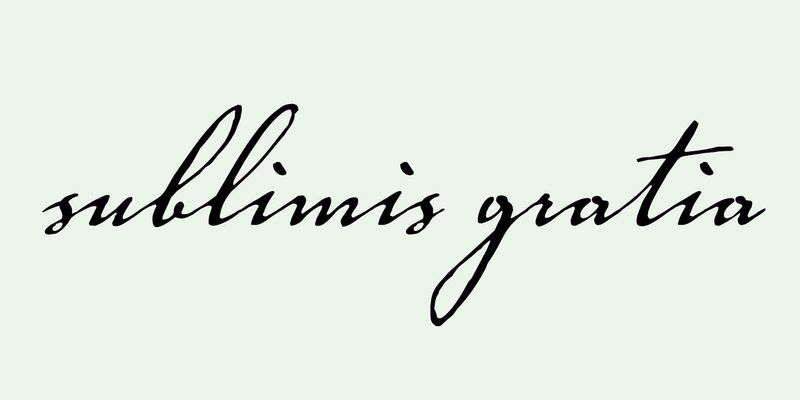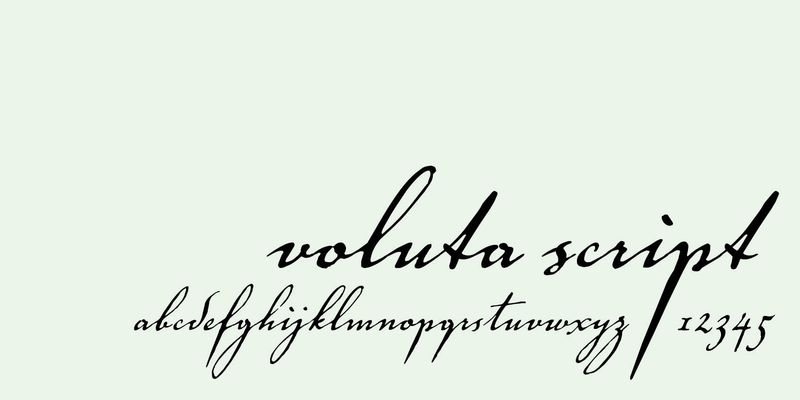
Австрийский дизайнер Виктор Зольт-Биттнер (Viktor Solt-Bittner) создал шрифт Voluta Script для Adobe Original в 1998 году. Шрифт предназначался для оформления путеводителя по Австрийской галерее в замке Бельведер. Штрихи Voluta Script напоминают волюту (от лат. «voluta») — орнамент в виде спирали или свитка, характерный для барочной архитектуры замка Бельведер. Этот замок был резиденцией принца Евгения Савойского, одного из великих полководцев 18 века, считающегося важной фигурой в истории Австрии. Зольт-Биттнера попросили создать шрифт, основанный на каллиграфии того времени, чтобы проиллюстрировать славный путь Евгения. Дизайнер обратился за вдохновением к немецкой позднесредневековой скорописи «куррент», выполненной в стиле готического курсива. Зольт-Биттнер создал гибридный стиль, в котором ритм штриха и основные формы букв сочетаются с большими заглавными буквами, темными вертикальными штрихами, начальными и конечными символами с пышными росчерками. Voluta Script помогает перенестись в эпоху барокко и придает величественное изящество современному набору шрифтов. Патенты США 413, 620; 424, 607.
Программа Adobe Originals была запущена в 1989 году в качестве внутренней шрифтовой мастерской Adobe, чтобы обеспечить исключительное качество, техническую точность и эстетическую долговечность создаваемых оригинальных гарнитур.
На сегодняшний день типографская команда Adobe создает сложные и даже экспериментальные шрифты, исследуя возможности дизайна и технологий. Гарнитуры, выпущенные под брендом Adobe Originals, являются результатом многолетней работы и исследований и признаны отраслевым стандартом за замысел и качество их разработки.